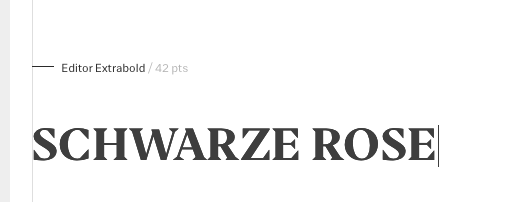
Wortmarke "Schwarze Rose"
ich bin auf der Suche nach der Schrift, die in folgender Wortmarke zur Anwendung kommt.
Entworfen wurde die Marke von Paperlux im Auftrag des Hemdenherstellers Seidensticker.
Leider finde ich nirgendwo Angaben zu der verwendeten Font.
Das beißt sich schon in der Frage. Wenn da was »entworfen« wurde, wurde etwas entworfen, also neu geschaffen. Dann ist die Frage nach der Schrift des Logos müßig. Oder willst du sagen, der Logo-Entwurf beinhaltete nichts weiter als eine Schrift aus dem Menü zu fischen und diese zu tippen
Danke für den Hinweis. Selbstverständlich habe ich schon auf anderen Wegen versucht zu recherchieren. Auf der Website sind leider nur Bilder eingebettet und die üblichen Seiten (What The Font, etc.) helfen leider auch nicht weiter.
Bitte entschuldige meinen Ausdruck. Ich weiß nur leider nicht, ob die Wortmarke exklusiv entworfen wurde. Ich gehe allerdings davon aus, dass es sich um eine bestehende Schrift handelt.
Könnte mit der "Editor" von der www.indiantypefoundry.com gesetzt sein.
Vielen Dank für den ersten brauchbaren Tipp! Kommt leider noch nicht ganz ran, ist aber eine mögliche Alternative.
So ist das nun mal, wenn man eine echte Text-Marke entwerfen möchte,
Entweder man
die paar Buchstaben, die man für das Logo braucht
t komplett frei, ohne das man sich einer fertigen Schriftart bedient wie bei diesem Beispiel, oder man
eine vorhandene Schrift, bis diese deutlich von der Ausgangsschrift abweicht. Hier habe ich eine meiner eigenen Schriftarten verändert.
Hiermit erreicht man, dass das Logo nicht von jedem einfach so nachgetippt werden kann, und es überhaupt als Marke schützbar ist.
Die Frage ist nicht unberechtigt. Wortmarken werden unentwegt aus Satzschriften hergestellt. Und die Arbeit mit Schrift ist durchaus Entwurfsarbeit. Ich finde »Wortmarken« (schon dieses Wort!) zwar an sich oft fad, aber so wird heute meistens entworfen.
Muss diese thesenhafte Verallgemeinerung sein? Damit tut man all denen Unrecht, die es heute eben nicht so machen.
Ich denke ich werde bei Paperlux mal anfragen oder vorerst mit der »EDITOR« Vorlieb nehmen.